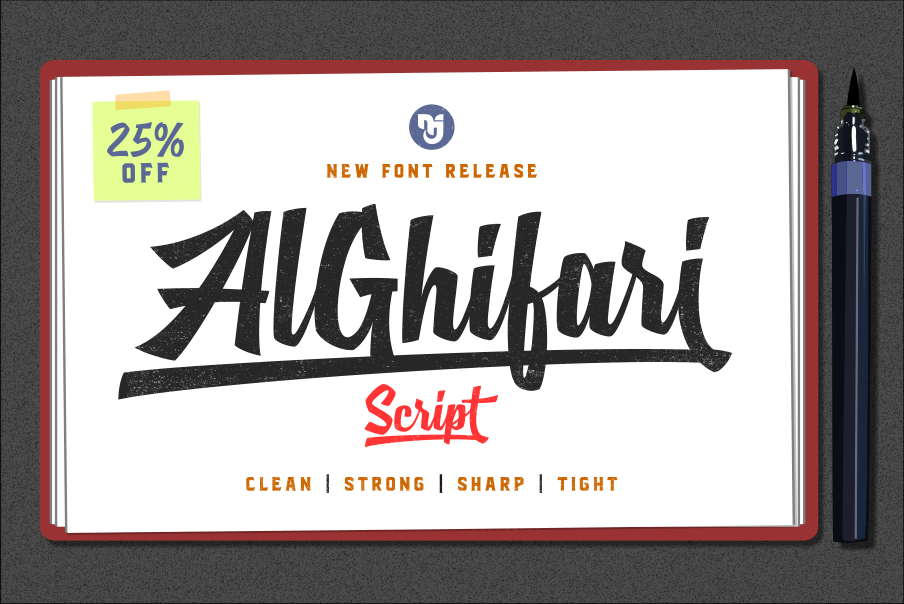
A MJ AlGhifari Font é uma elegante escrita livre inspirada nas linhas esculpidas por penhaqueiros. Inspirada nos traços finos e bem definidos do estilo de Hamilton, esta fonte adquire um tom mais sóbrio e firme. Ela consegue equilibrar a suavidade da escrita com uma estrutura firme e apertada, proporcionando um aspecto forte que mantém o seu caráter natural, sem perder a autenticidade de uma escrita a mão. Ideal para ambientes onde se busca um estilo elegante e profissional, esta fonte é perfeita para qualquer projeto que valorize uma escrita artesanal delicada.